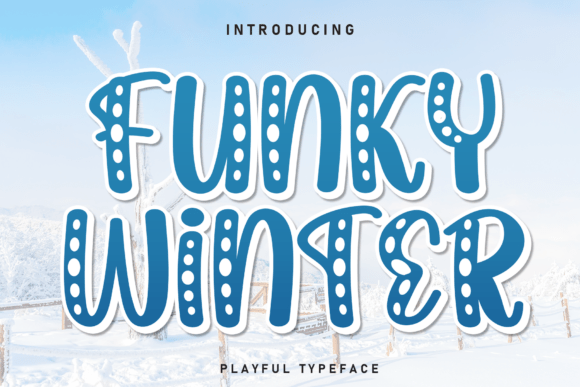
Funky Winter
Funky Winter – A Fonte Criativa que Transforma Seus Projetos de Inverno
Se você está em busca de tipografia exclusiva para dar um toque moderno e divertido às suas criações de inverno, a Funky Winter chega como a solução perfeita. Esta fonte foi desenvolvida para quem valoriza estilo, legibilidade e versatilidade, proporcionando experiências extraordinárias em cada aplicação.
Por que escolher a Funky Winter?
- Design contemporâneo: letras estilizadas que combinam elegância e ousadia, ideais para convites de casamento, embalagens de produtos e posts de redes sociais.
Aplicações Ideais da Funky Winter
A versatilidade da Funky Winter a torna indispensável em diversos contextos:
- Exposições de parede e sinalização de ponto de venda;
- Convites de casamento e eventos temáticos de inverno;
- Logotipos e identidade visual para campanhas de mídia social;
- Rótulos, embalagens e design de produtos sazonais;
- Watermarks e marcas d'água em fotografias profissionais;
- Materiais de papelaria, como cartões, papel timbrado e folhetos;
- Qualquer projeto que exija handwriting elegante e com personalidade.